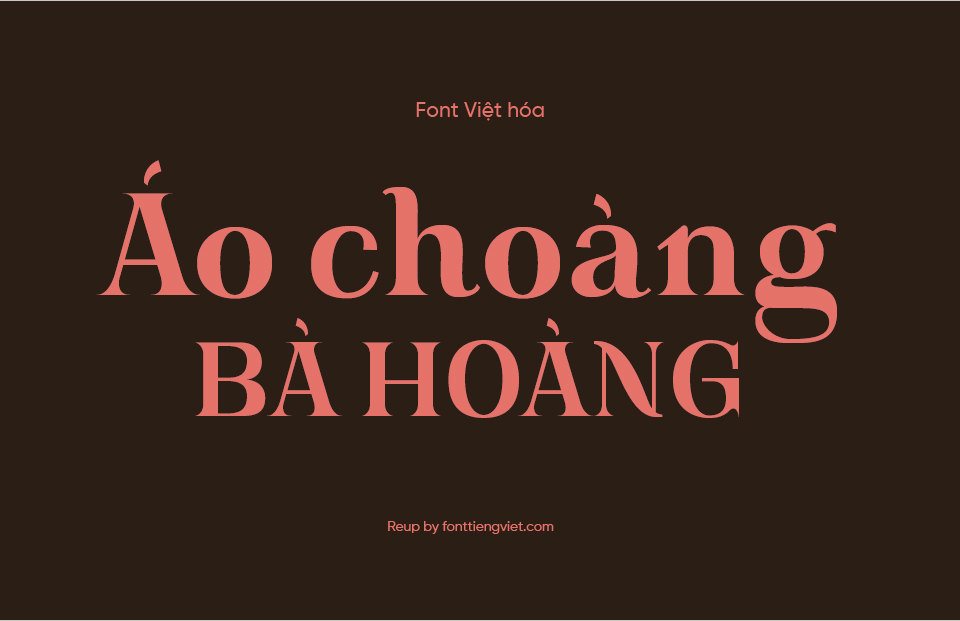
Trong thế giới thiết kế đồ họa và typography, việc tìm kiếm một bộ Font Chữ đẹp, độc đáo và đặc biệt là đã được Việt hóa luôn là ưu tiên hàng đầu. Một trong những cái tên đang làm mưa làm gió trong cộng đồng sáng tạo gần đây chính là Font Việt hóa MTD Gorni. Bộ font này không chỉ mang đến vẻ đẹp cổ điển, sang trọng mà còn được tối ưu hóa hoàn hảo cho tiếng Việt, giúp các dự án của bạn trở nên chuyên nghiệp và cuốn hút hơn bao giờ hết. Bài viết này sẽ đi sâu vào nguồn gốc, đặc điểm nổi bật và lý do tại sao bạn nên sở hữu bộ font tuyệt vời này.
Giới thiệu chi tiết về Font Việt hóa MTD Gorni
Bộ font MTD Gorni, trước khi được Việt hóa, đã nổi tiếng trong giới typography quốc tế nhờ sự kết hợp hài hòa giữa nét cổ điển và hiện đại. Font này thuộc nhóm serif, nhưng các đường nét lại được xử lý tinh xảo, mang lại cảm giác nhẹ nhàng, thanh lịch. Phiên bản Việt hóa do MTD thực hiện đã giữ nguyên được tinh thần đó, đồng thời bổ sung đầy đủ các ký tự tiếng Việt có dấu, một yếu tố cực kỳ quan trọng đối với các nhà thiết kế tại Việt Nam.
Nguồn gốc và phong cách thiết kế của Font Gorni
Font Gorni được lấy cảm hứng từ những bản in cổ điển, mang đậm dấu ấn của nghệ thuật in ấn Châu Âu thế kỷ trước. Nó sở hữu các nét đậm mỏng rõ ràng, tạo độ tương phản cao, giúp văn bản dễ đọc và có tính thẩm mỹ vượt trội. Đây là lý do tại sao font này thường được lựa chọn cho các ấn phẩm cao cấp như tạp chí thời trang, thương hiệu mỹ phẩm, hoặc các tài liệu mang tính chất trang trọng. Sự tỉ mỉ trong từng đường cong, từng đầu serif nhỏ đã biến Gorni trở thành một biểu tượng của sự sang trọng và tinh tế trong typography hiện đại.
Đặc điểm nổi bật của phiên bản Việt hóa (hỗ trợ đầy đủ dấu)
Điều làm nên giá trị đặc biệt của Font Việt hóa MTD Gorni chính là sự hoàn thiện về mặt ngôn ngữ. Quá trình Việt hóa không chỉ đơn thuần là thêm dấu mà còn là việc căn chỉnh lại khoảng cách giữa các ký tự (kerning) và chiều cao chữ (x-height) để khi kết hợp với các dấu thanh, dấu mũ, văn bản vẫn giữ được sự cân đối, không bị gãy nét hay mất thẩm mỹ. Nhờ đó, dù bạn đang soạn thảo một bài luận phức tạp cho học sinh, một tài liệu quảng cáo hay một quyển sách, font này đều đáp ứng được yêu cầu khắt khe nhất về độ rõ ràng và tính thẩm mỹ. Đây là một lợi thế lớn so với các font nước ngoài chưa được tối ưu hóa.
Ứng dụng của Font MTD Gorni trong thiết kế
Sự linh hoạt là một trong những ưu điểm lớn nhất của bộ font MTD Gorni. Dù bạn là một học sinh đang chuẩn bị bìa tiểu luận, một sinh viên cần thiết kế infographic chuyên nghiệp, hay một chuyên gia thiết kế đồ họa, font này đều có thể trở thành công cụ đắc lực.
Nó đặc biệt phù hợp cho các tiêu đề lớn, logo thương hiệu, hoặc các đoạn văn bản cần sự nhấn mạnh cao. Khi kết hợp với các font sans-serif tối giản khác, MTD Gorni tạo ra một sự đối lập thú vị, làm nổi bật thông điệp chính mà bạn muốn truyền tải. Các nhà thiết kế web cũng thường sử dụng font này cho các yếu tố branding để tạo nên một dấu ấn độc quyền.
Phù hợp với học sinh, sinh viên và các ấn phẩm học thuật
Đối với học sinh cấp 3 chuẩn bị cho kỳ thi tốt nghiệp hoặc sinh viên đại học thường xuyên phải làm báo cáo, việc sử dụng một font chữ đẹp và chuyên nghiệp là vô cùng quan trọng. Font Việt hóa MTD Gorni mang lại sự trang trọng cần thiết cho các tài liệu học thuật. Thay vì sử dụng những font phổ thông đã quá quen thuộc, việc lựa chọn Gorni sẽ giúp tài liệu của bạn nổi bật hơn, thể hiện sự đầu tư nghiêm túc vào hình thức. Điều này đặc biệt hữu ích khi thiết kế các poster, slide thuyết trình hoặc bìa sách kỷ yếu.
Hơn nữa, nhờ độ tương phản cao, font Gorni còn cải thiện trải nghiệm đọc, giúp các bài thi thử hoặc tài liệu ôn tập của các bạn học sinh được trình bày rõ ràng, dễ theo dõi hơn. Đây thực sự là một “vũ khí bí mật” giúp nâng cao chất lượng thẩm mỹ của mọi ấn phẩm liên quan đến giáo dục và đào tạo.